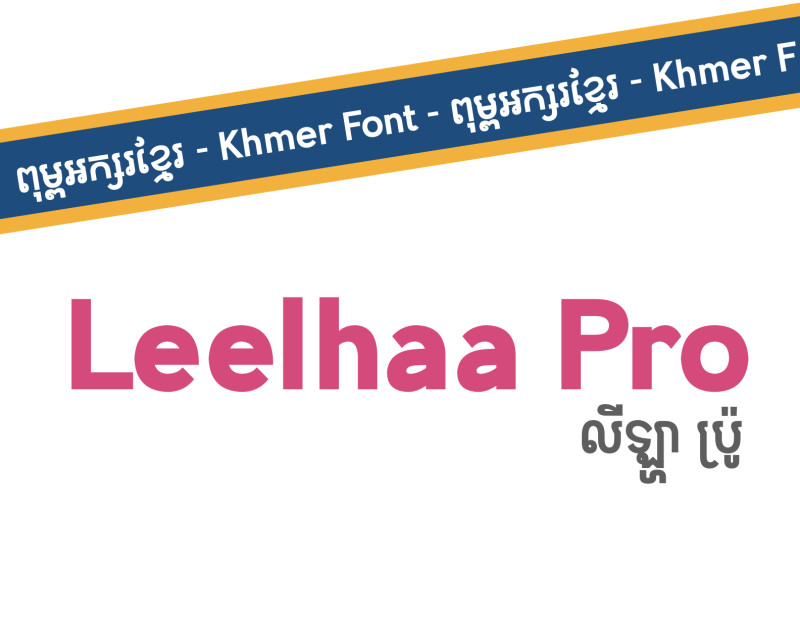
Leelhaa Pro [Family] Premium Pack (12 fonts)
Complete packaged (12 fonts) product featuring sans serif glyphs and true italics in 6 font weights for the Khmer and Latin script
ពុម្ពអក្សរដ៏ស្រស់ស្អាតដែលបានរចនាឡើងឲ្យមានអំណានល្អប្រសើរ និងភាពទស្សនាមុតមាំហៅថា Leelhaa Pro - មានកម្រស់ ៦ ប្រភេទ ខុសៗគ្នាពី ធម្មតា ដល់ ខ្មៅ! កញ្ចប់បុព្វលាភនេះមាន អក្សរឈរ និង អក្សរទ្រេតពិត សរុបចំនួន ពុម្ពអក្សរ ១២ មុខប្រើសម្រាប់ការបង្កើត ក្រាហ្វិច ការផ្សាយពាណិជ្ជកម្ម និមិត្តសញ្ញា និង ស្លាកយីហោដ៏ស្រស់ស្អាត ដែលសមស្របជាអក្សរធំបង្ហាញ ឬក៏អក្សរក្នុងអត្ថបទ។
[កញ្ចប់នេះមានគ្រប់ពុម្ពអក្សររបស់ Leelhaa ទាំងអស់ ៦ពុម្ពអក្សរជាអក្សរឈរ និង ៦ពុម្ពអក្សរគឺជា អក្សរទ្រេត = សរុប ១២ ពុម្ពអក្សរ]
ដោយប្រើ Leelhaa Pro អ្នកអាចសរសេរអក្សរខ្មែរ និងអក្សរឡាតាំងយ៉ាងស្រស់ស្អាត។
1. Regular & Italic
2. Medium & Medium Italic
3. Demibold & Demibold Italic
4. Bold & Bold Italic
5. Ultrabold & Ultrabold Italic
6. Black & Black Italic
Leelhaa Pro, the beautiful Khmer typeface designed for high readability and visibility - features 6 different weight class from Regular to Black. This premium package contains regular and true Italic glyphs, a TOTAL OF 12 FONT styles for you to create beautiful graphics, advertisements, logos, and banners that is ideal for Display and Text.
[THIS PACK FEATURES ALL LEELHAA FONTS - 6 REGULAR FONTS AND 6 ITALIC FONTS = TOTAL 12 FONTS]
With Leelhaa Pro, you can beautifully write in Khmer and Latin.
1. Regular & Italic
2. Medium & Medium Italic
3. Demibold & Demibold Italic
4. Bold & Bold Italic
5. Ultrabold & Ultrabold Italic
6. Black & Black Italic